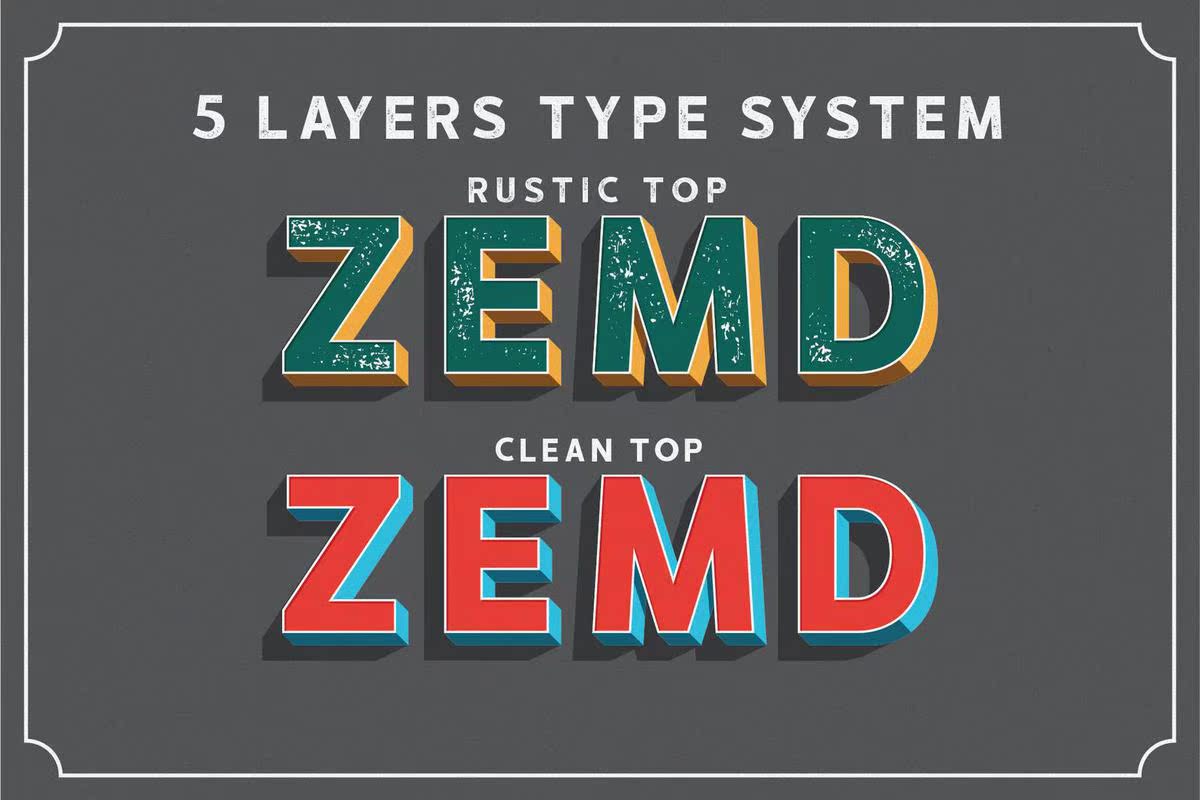
Hustle采用5层系统的显示字体,采用2种风格(干净和质朴)。采用5层系统时,此字体有多种可能的变化。使用RightictPlayer时,Hustle具有一种电动汽车工业触感,但同时还具有一种带清洁层的现代感。Hustle采用5层系统的显示字体,使用2种风格(干净和质朴)的游戏机。使用5层系统,这款Font有许多可能的变化。使用JusticToPlayer,Hustle拥有一种电动工业触感,同时还可以使用清洁的顶层。